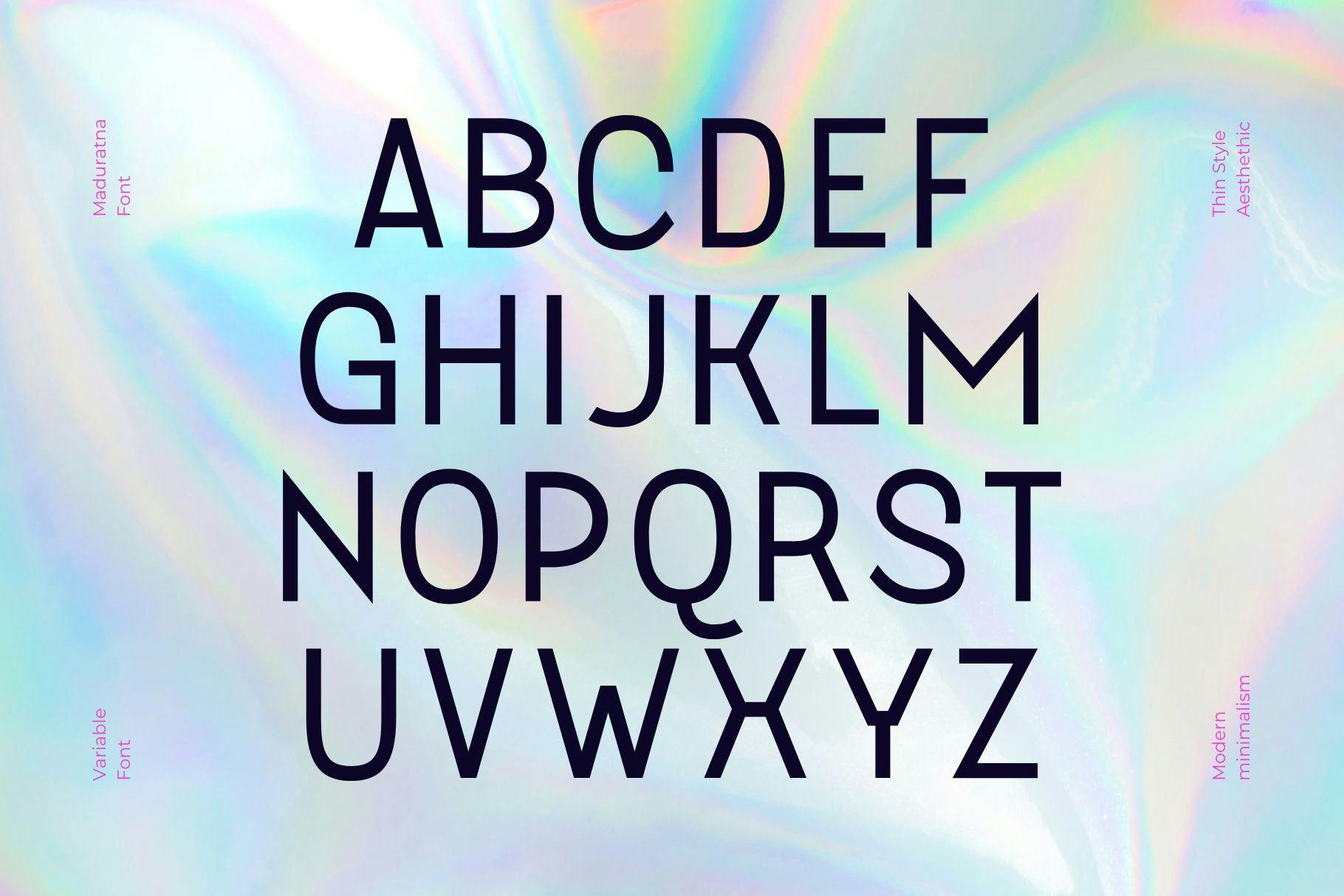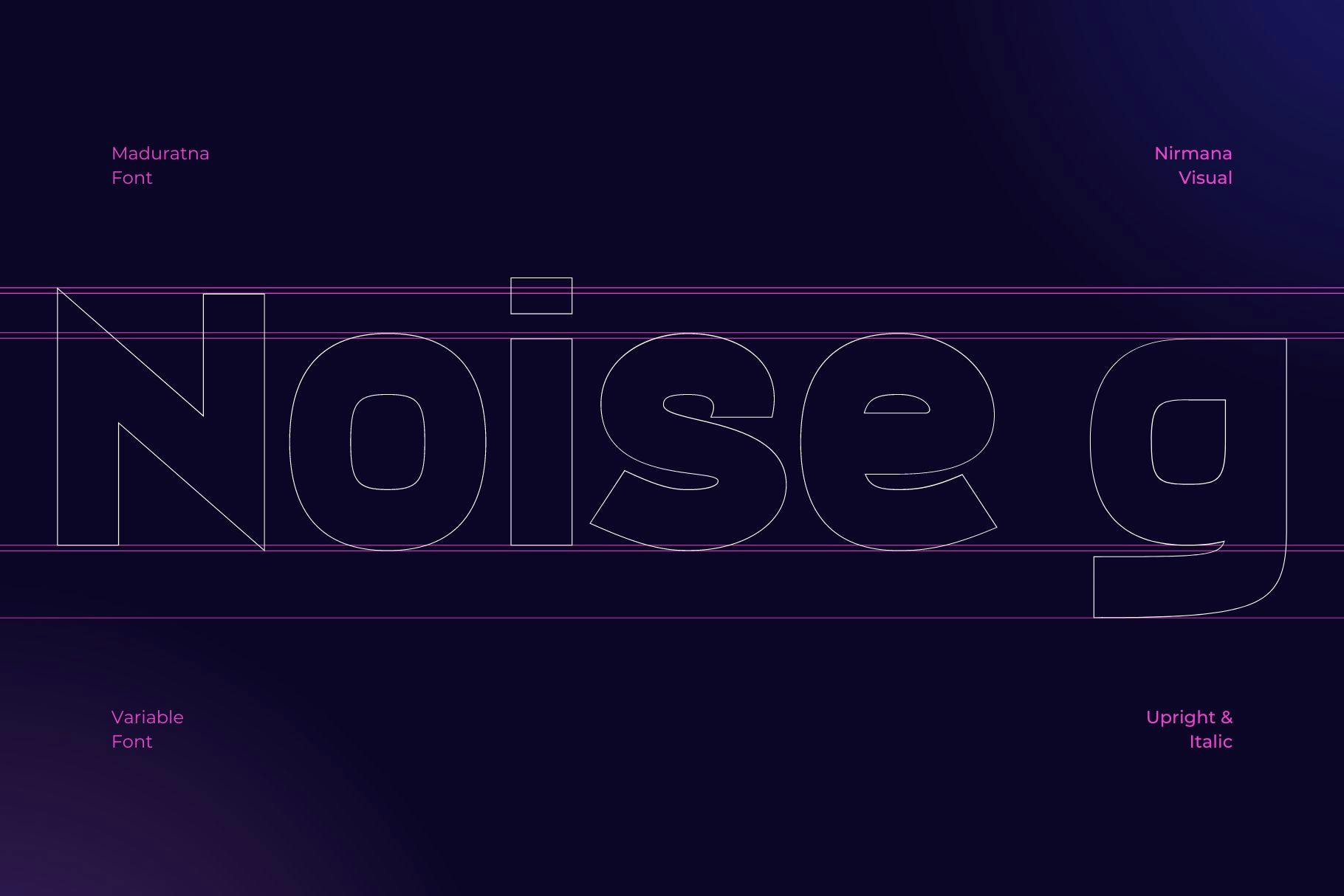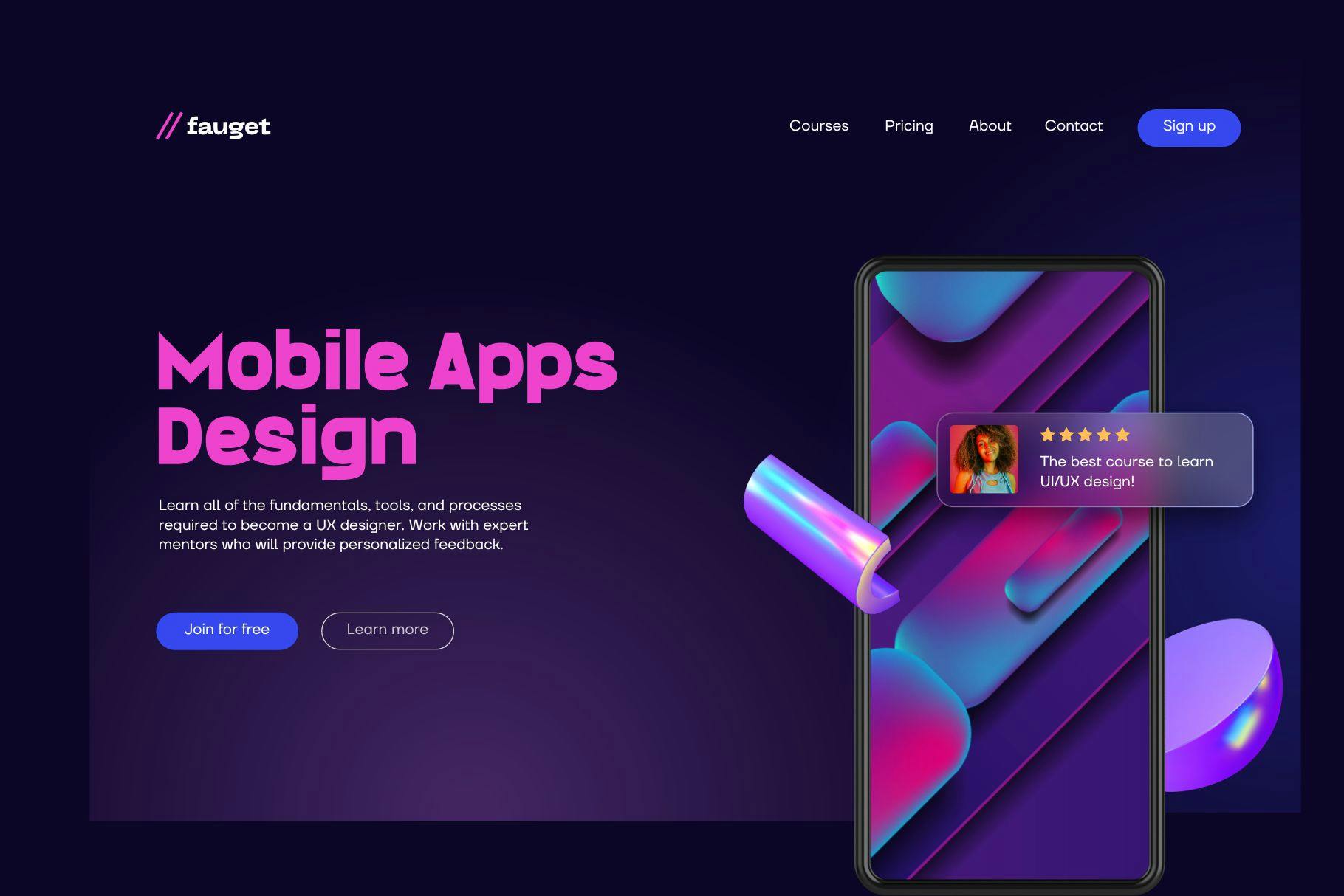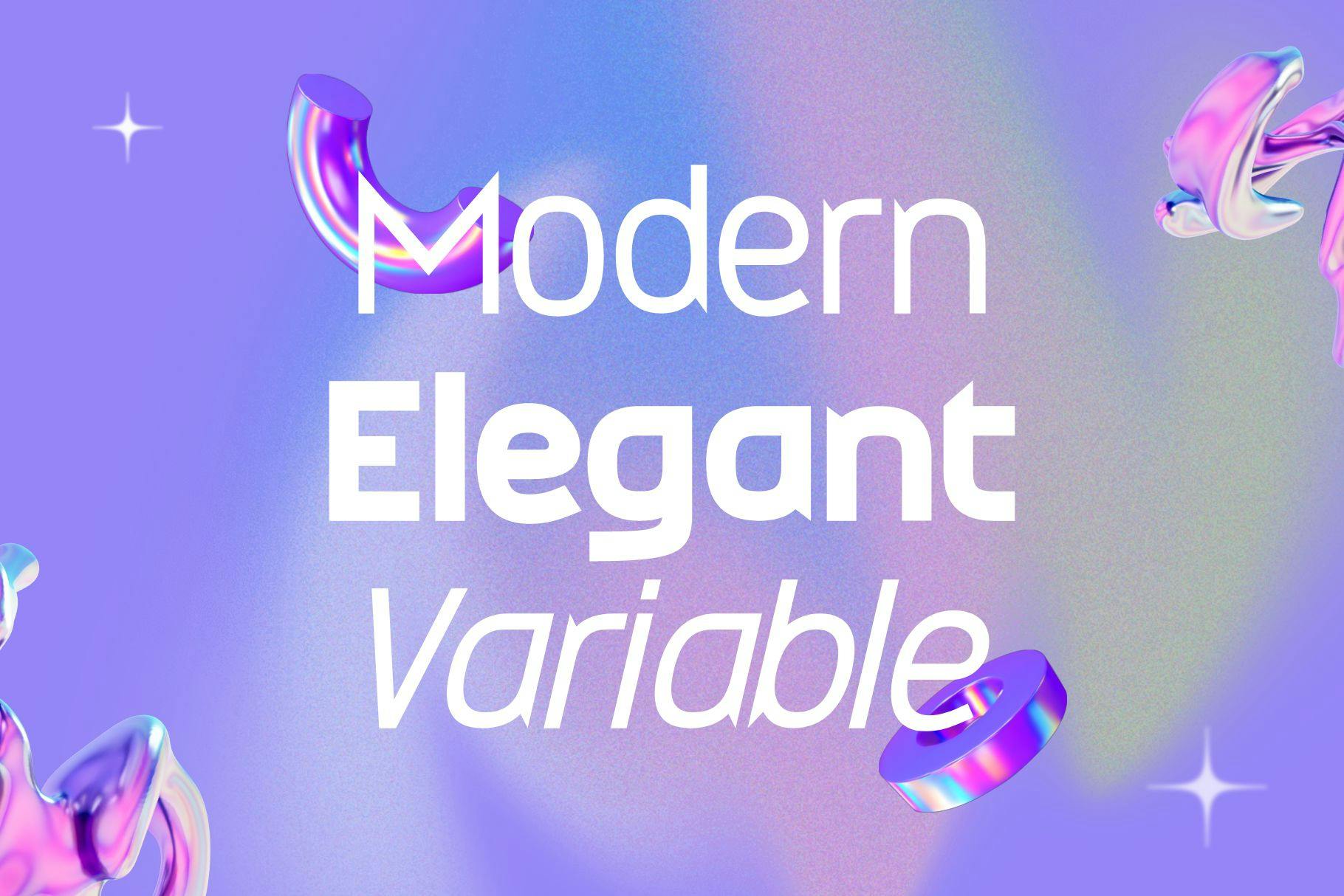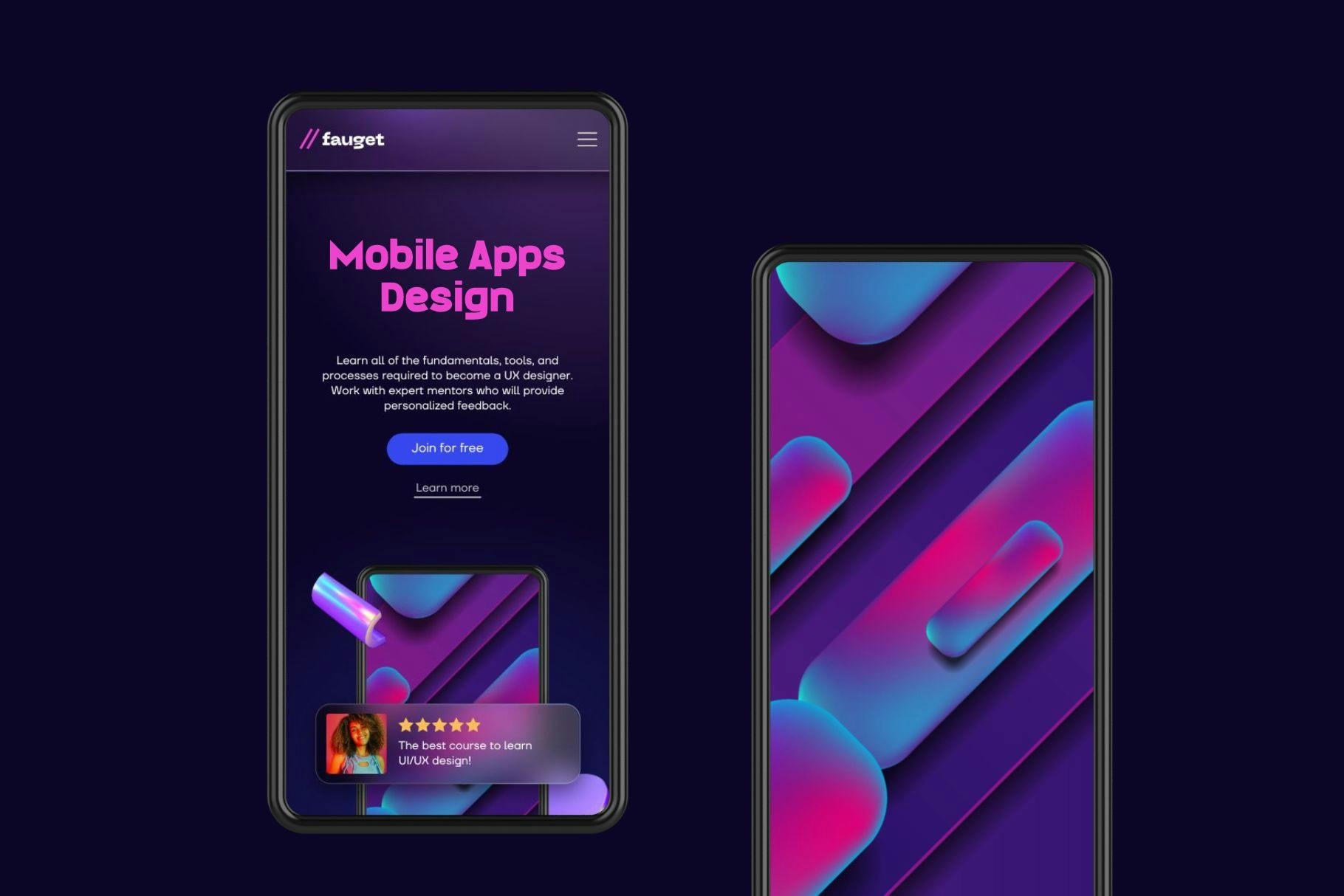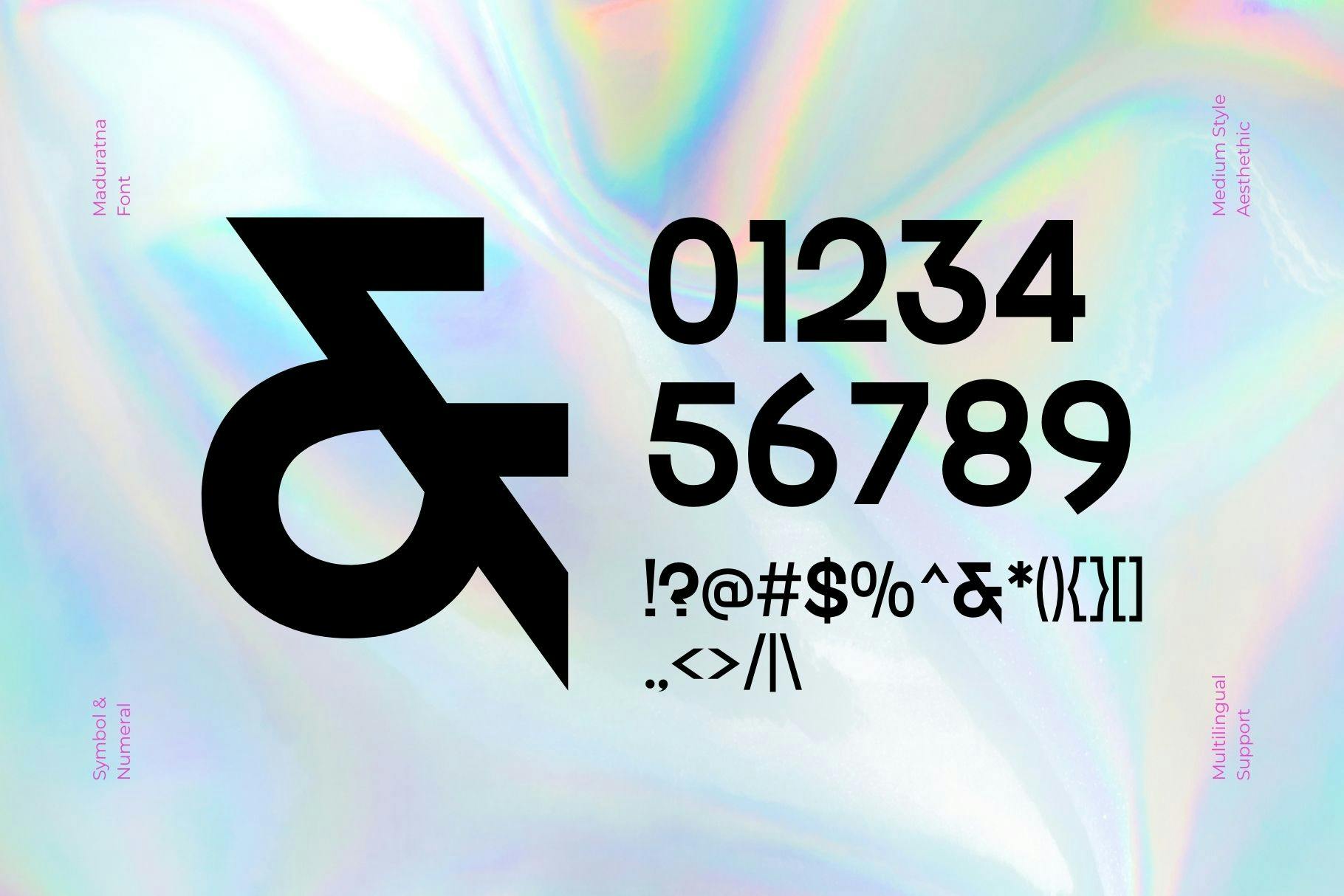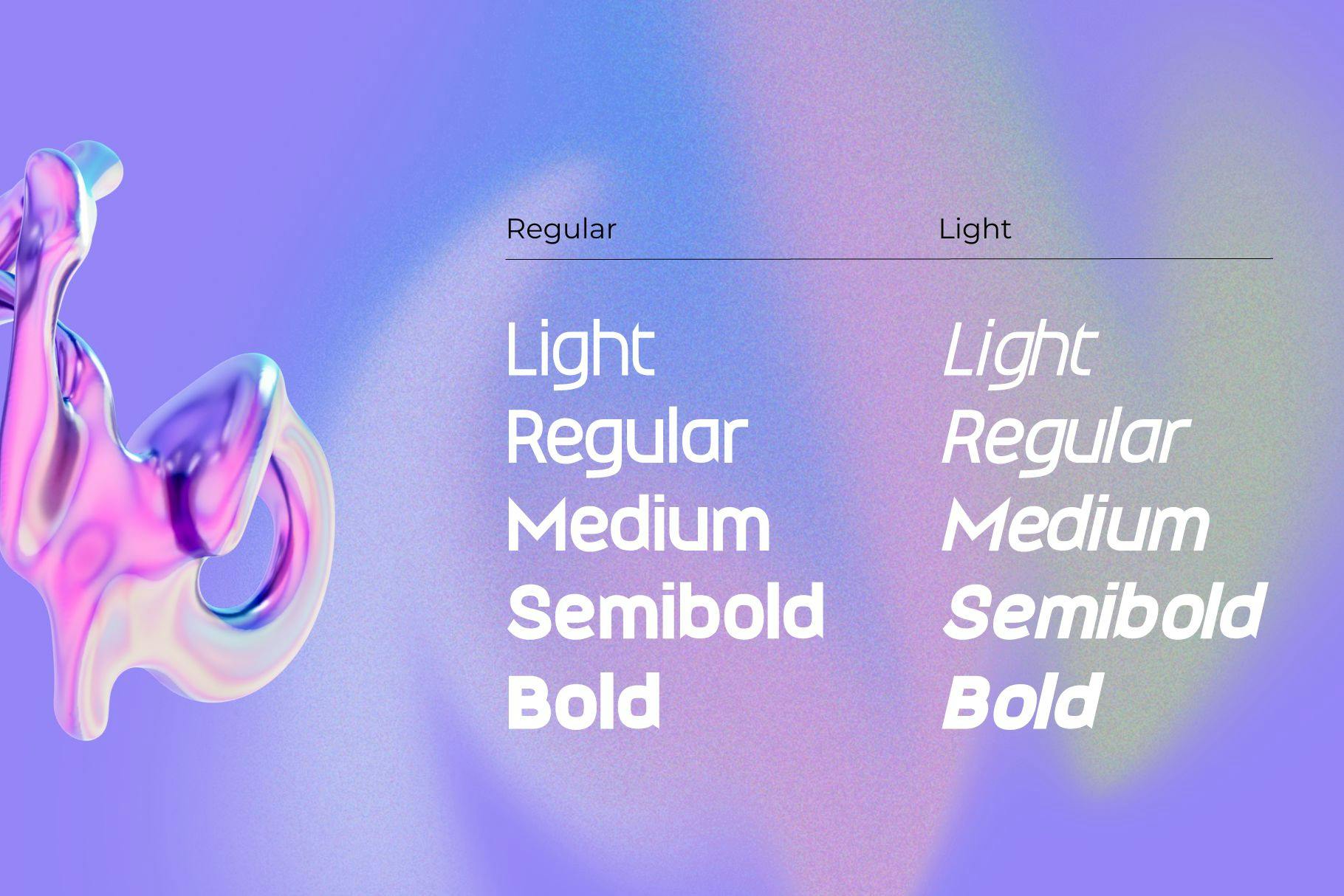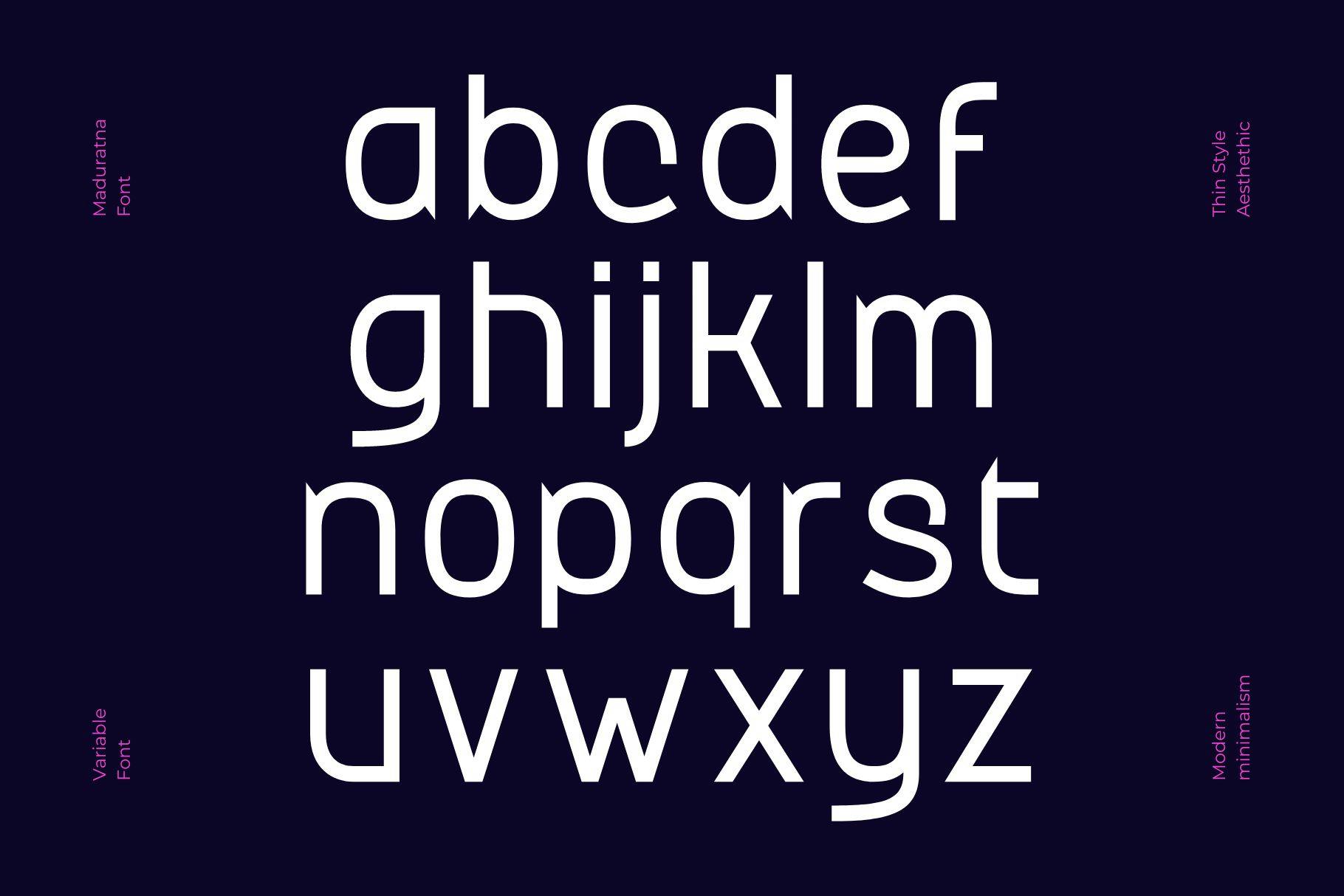
مدوراتنا یک خانواده فونت سنس سریف منحصر به فرد و بازیگوش با ۵ وزن است.
این فونت هارمونی زیبای تایپوگرافی را برای پروژههای طراحی متنوع از جمله لوگو و برندینگ، پستهای شبکههای اجتماعی، تبلیغات و طراحی محصولات ارائه میدهد.